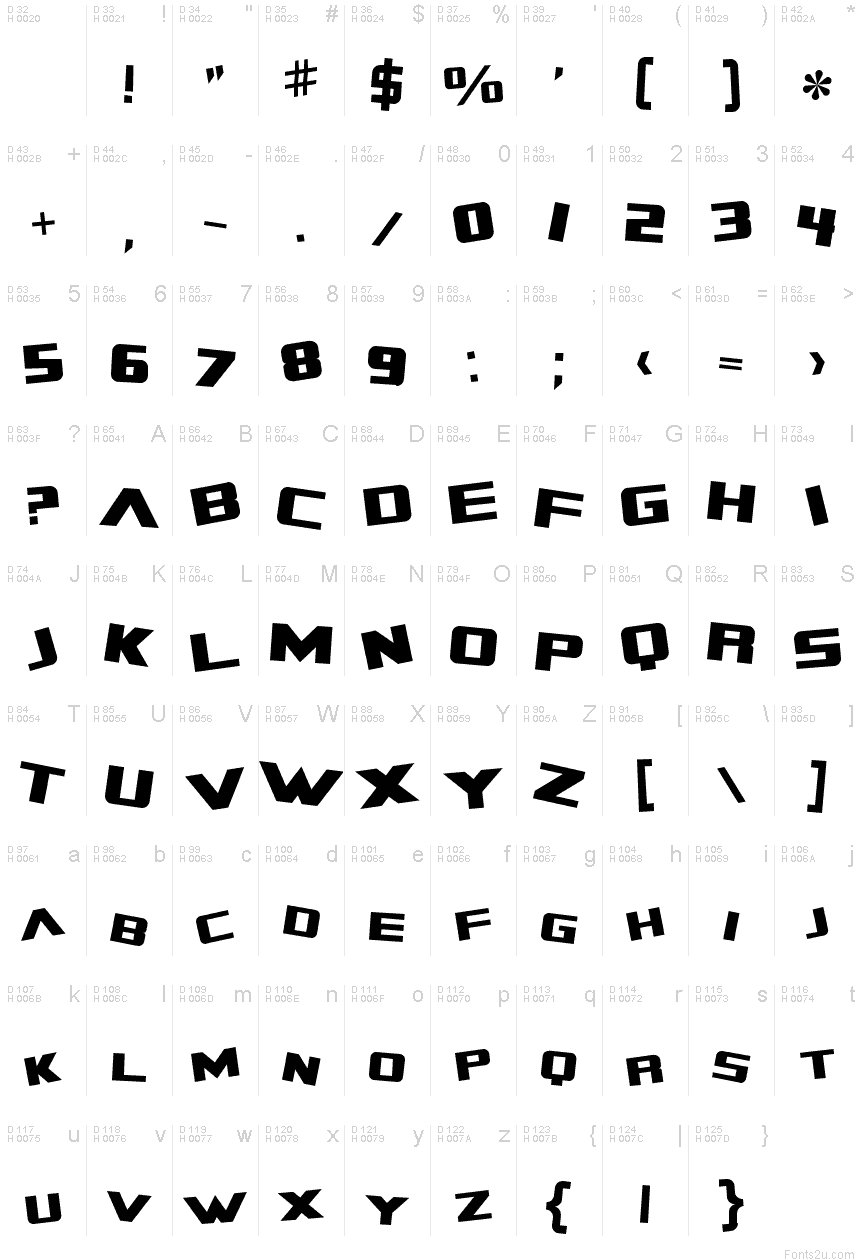
تجسد خط Zero Gravity Extended، وهو خط عرض مجاني بنمط الخيال العلمي من تصميم ShyWedge صدر عام 1999، أجواء التكنو في أواخر التسعينيات بحروف استهلالية كبيرة ومائلة ووقفة غير مستقرة بشكل متعمد. تبدو الحروف كأنها ممطوطة وملتوية، حيث تمزج بين الهندسة الحادة وارتجاف خفيف يجعلك تشعر وكأن النص ينجرف بعيداً عن محوره.
هذا يجعل الخط خياراً طبيعياً لشعارات الألعاب، ومنشورات النوادي، وعناوين الملصقات، وأغلفة المجلات، وبطاقات العناوين حيث تكون الحركة أكثر أهمية من الصقل. استخدمه في النصوص القصيرة، أو الشعارات المختصرة، أو كعنصر ترويج بصري عندما تريد أن تشعر بأن الحروف ميكانيكية، وغير متوازنة، وتتمتع بلمسة من انعدام الوزن.